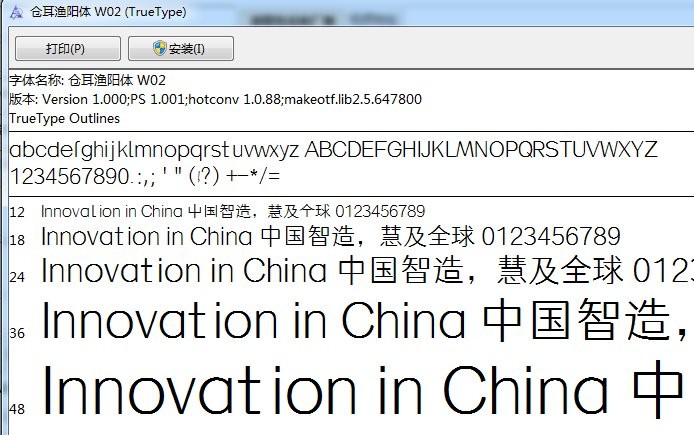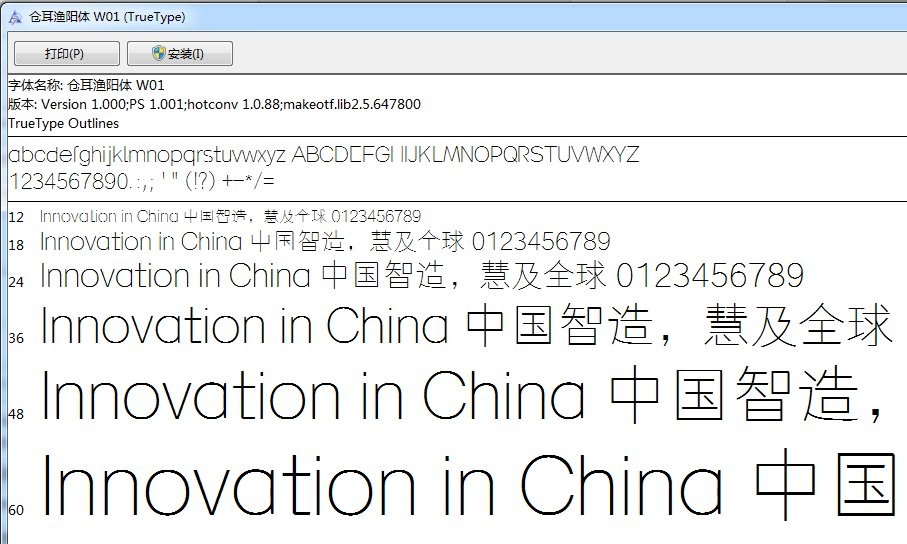
站酷仓耳渔阳体ttf
站酷仓耳渔阳体ttf是可以免费使用的公益字体,小编提供的安装包中包含了五个完整的ttf字体包,大家下载之后安装给出的方法进行操作,很快就能安装成功,这款字体给人的感觉比较端庄大气,方正规矩的字形看上去很舒适,可以用于多种场景。
仓耳渔阳体字体介绍:
站酷仓耳渔阳体是站酷冠名首款家族字体,5字重助你灵感跳动,为造福社会奉上的一份礼物,也是站酷冠名的首款拥有家族字体的公益字库!
站酷仓耳渔阳体
字体特色:
结合宋、黑二体的结构特点。
将部分笔画转折处做圆角处理。
方圆结合,厚重又不失灵动。